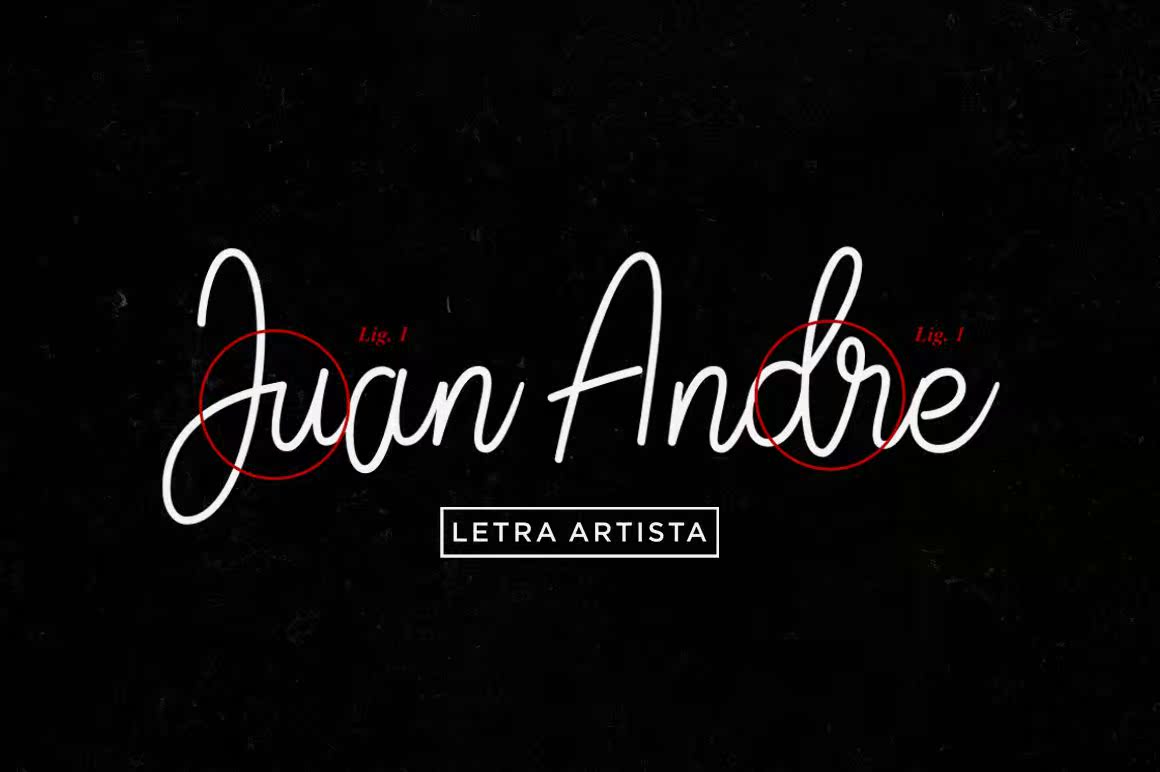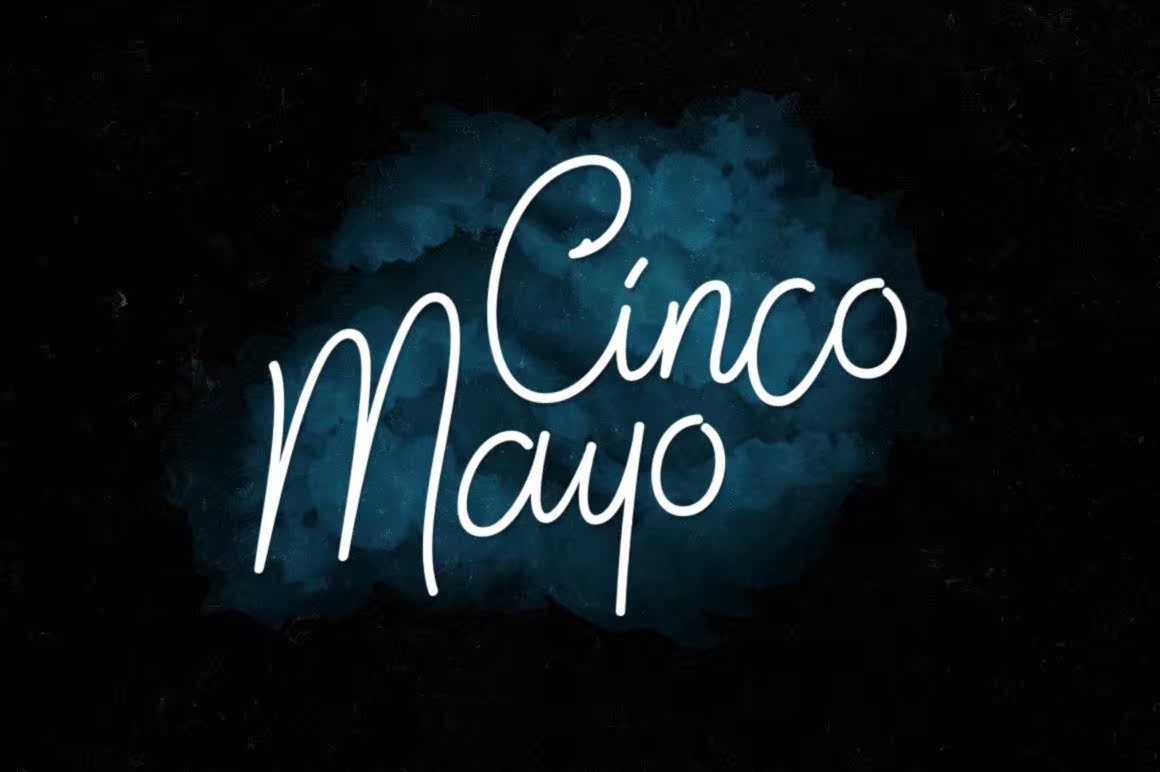
JaliscoisatingSignatureStyled手写手感、西装笔感、tumblr quotishdesign、magazinecover、服装/服装设计、Hipster包装设计、标识等。此功能字体可在.OTFand.TTF.中使用。JaliscoisatingStyled手写手感、西装笔感、tumblr quotishdesign、magazinecover、服装/服装设计、,Hipster包装设计、标识等。此Funky字体在.OTFand.TTF中提供。